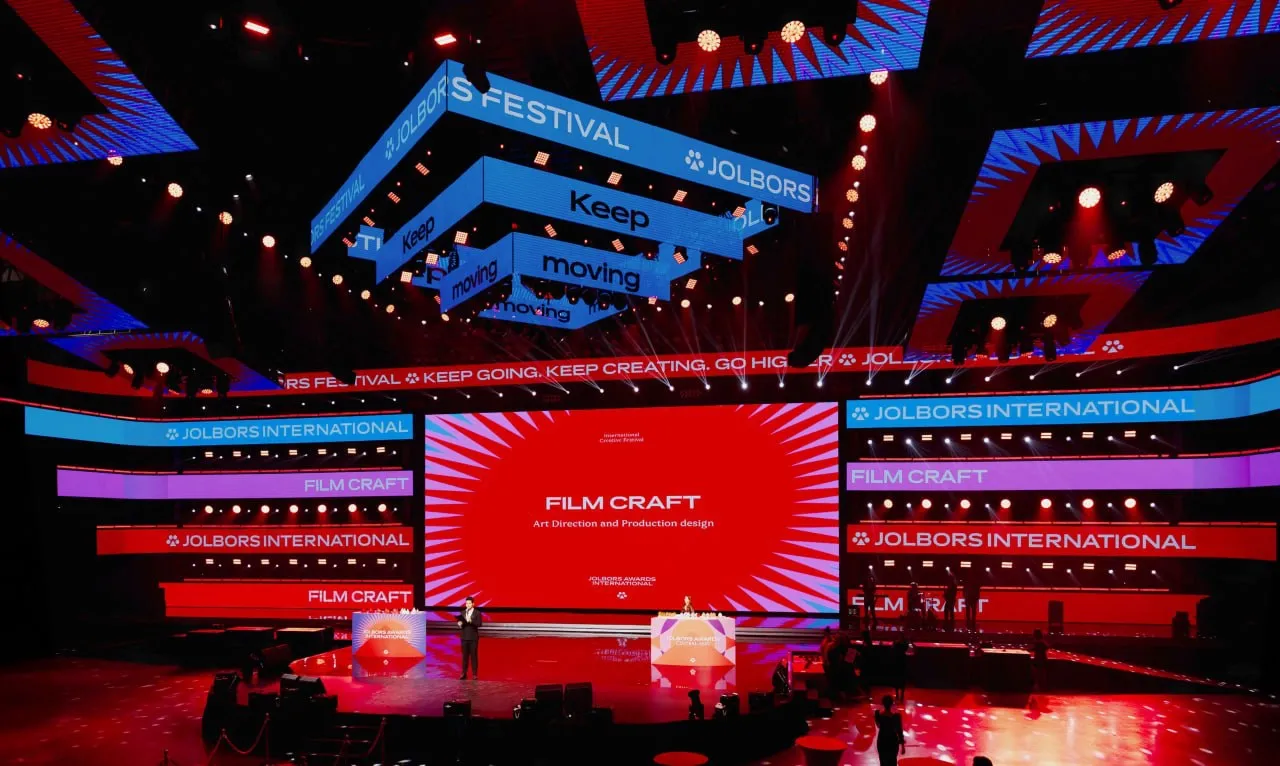
CoFo Weather Variable
CoFo Weather
О шрифте CoFo Weather
CoFo Weather—переменчивый шрифт, который ни секунды не стоит на месте: он то растягивается, то наклоняется. Weather создан для штормов и потрясений, его сильный и динамичный характер добавит остроты поворотам ваших проектов. А диапазон по жирности дополнительно расширяет шрифт до 60-ти начертаний, которые собраны в одном вариативном файле.
Благодаря тому, что знаки одной ширины нарисованы на одной и той же кегельной площадке, Weather позволяет вам менять насыщенность без корректировок макета, что делает его идеальным претендентом для работы где угодно, от анимаций до интерфейлов. Независимо от того, используете ли вы его как акцидентный шрифт или для основного текста (прямо посередине осей в вариативном шрифте), Weather готов внести живость в ситуацию. И самое интересное: Weather только начинает свой путь к росту и поиску своего уникального стиля. Доставайте зонтики и вперёд с восточным ветром!